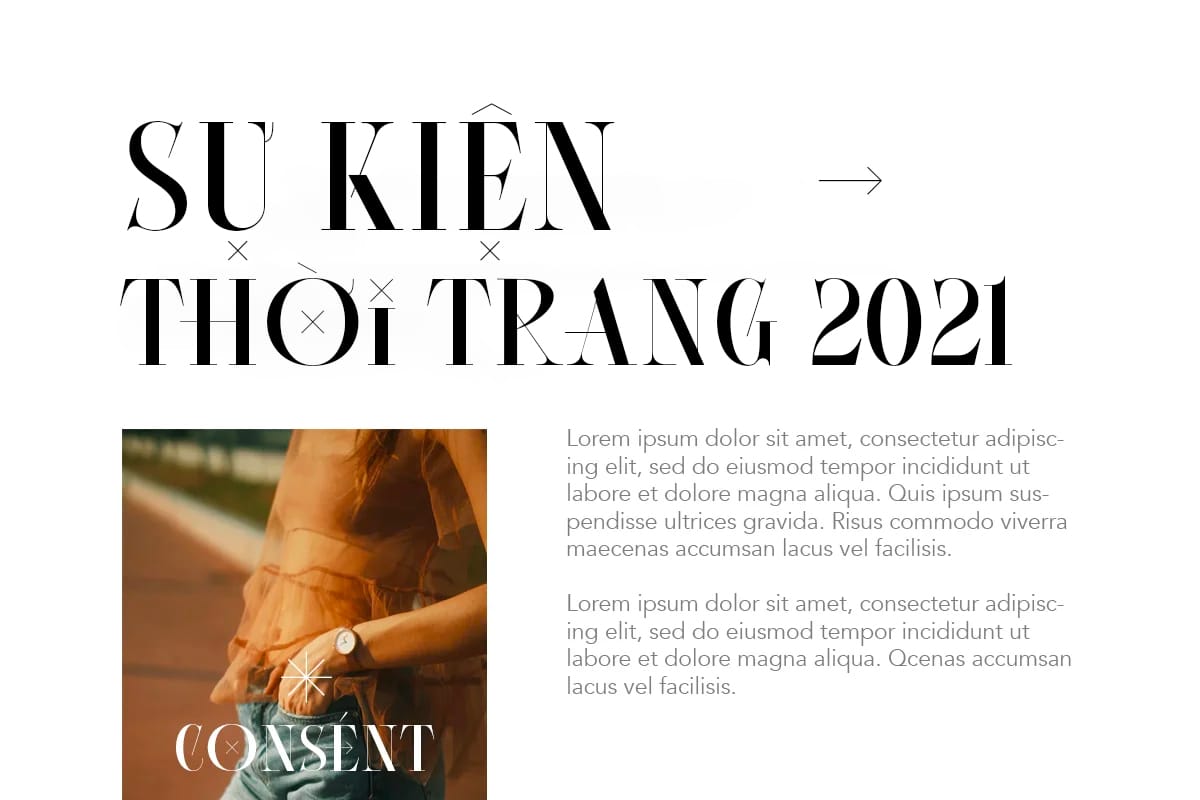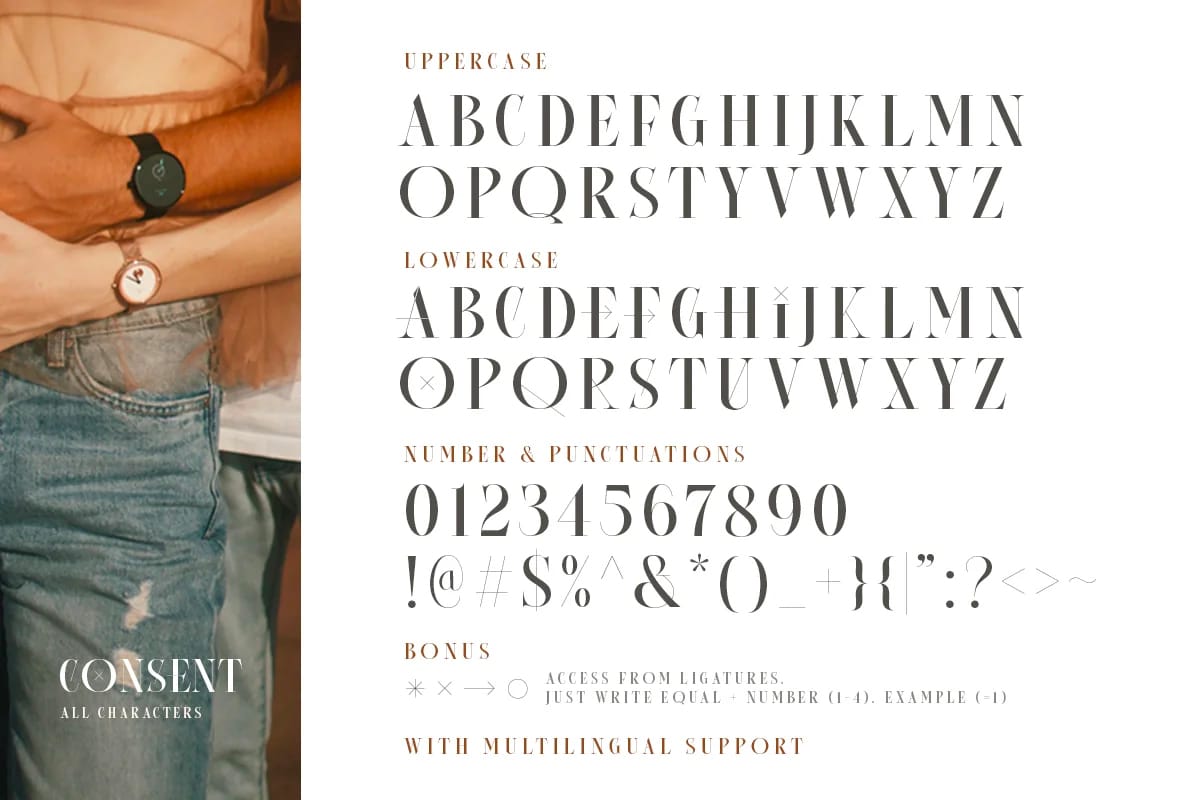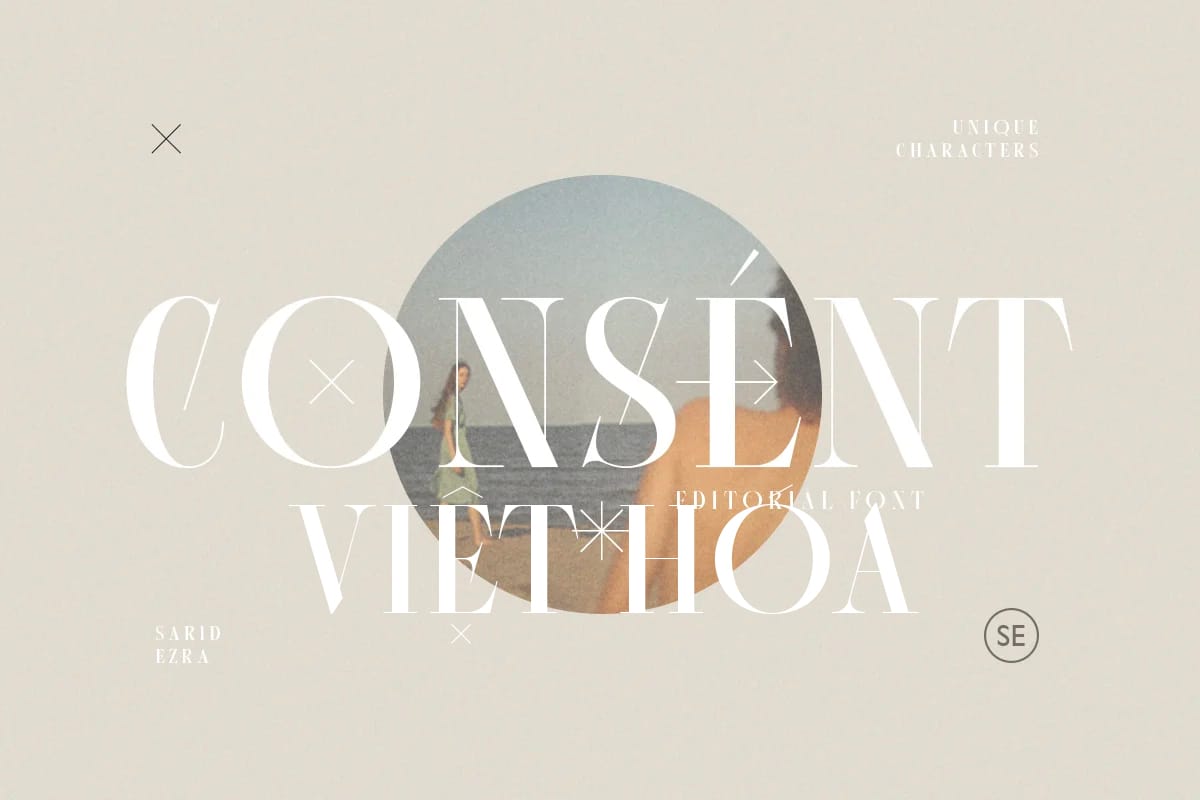
Consent là một font chữ serif biên tập với chữ hoa duy nhất. Với những tính năng đặc biệt, Consent sẽ làm cho thiết kế của bạn trở nên nổi bật và trang nhã hơn. Font chữ này phù hợp với thương hiệu hoặc tiêu đề của tạp chí. Bạn cũng có thể sử dụng font chữ này cho logo, thương hiệu và cũng có thể linh hoạt cho bất kỳ dự án nào! Không cần một bước phức tạp để sử dụng các tính năng. Chỉ cần nhập chữ thường, chữ hoa hoặc cả hai!